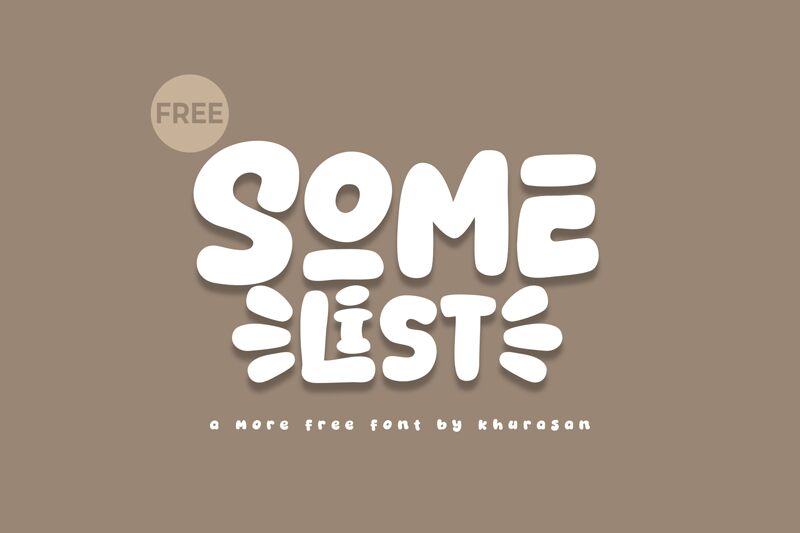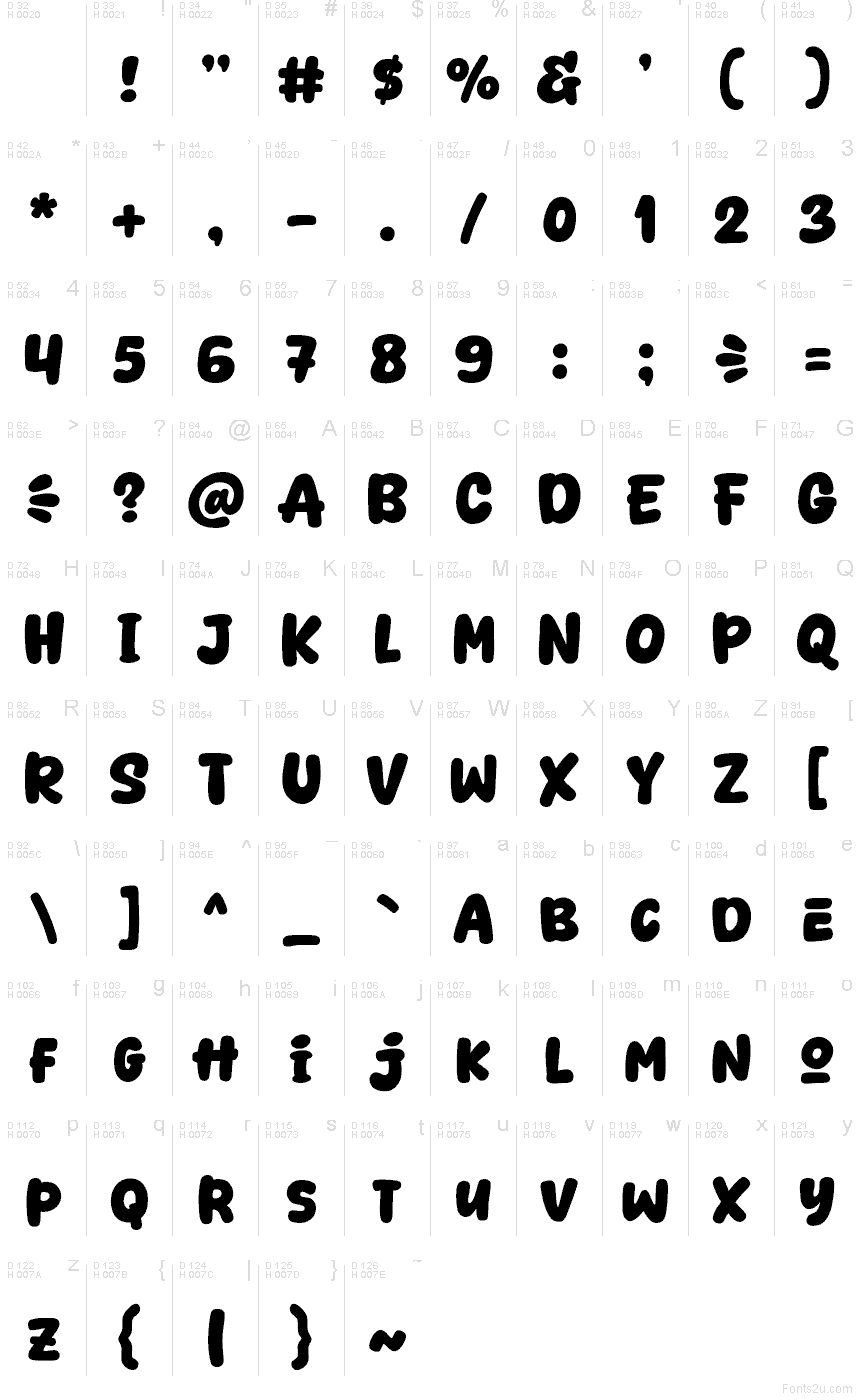
Somelist od Khurasan je bezplatné kreslené písmo typu display s kulatými, bublinovitými tvary a měkkými, nepravidelnými okraji, které působí jako vystřihované z papíru. Má široké a jednoduché znaky; hravý vzhled písmen O a E dodává celému nápisu přátelský a bezprostřední výraz.
Somelist skvěle funguje na dětských obalech, titulech plakátů, logách, pozvánkách na oslavy či etiketách na pochutiny, protože jeho kypré křivky působí vesele bez potřeby dalšího zdobení. Toto bezplatné písmo se také hodí pro hravé nálepky nebo krátké názvy produktů, kde zaoblené tvary dokážou samy o sobě definovat design.